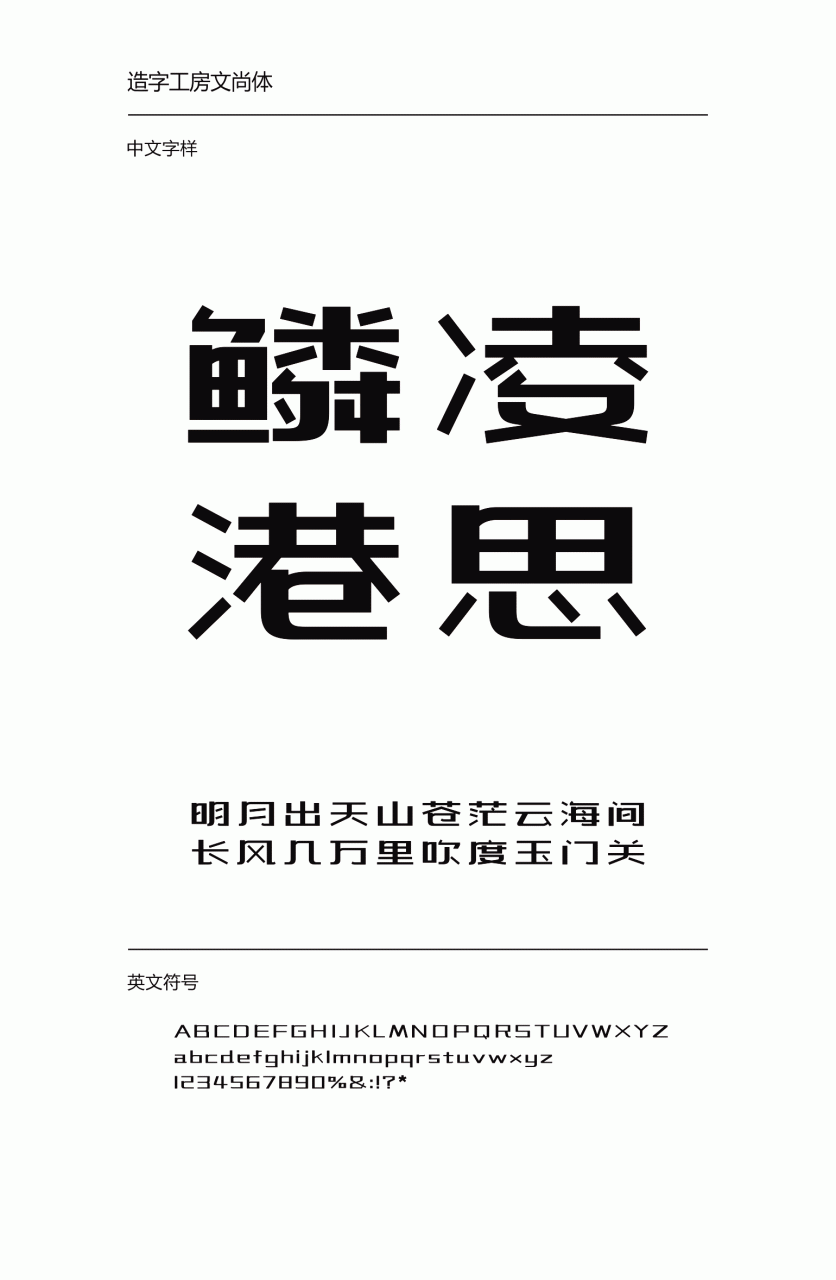
造字工房文尚体,其创意设计风格源于上世纪手绘美术字形,字形扁平,线条粗细变化明显,跌宕有致,短横的倾斜处理,让字形更加个性十足,风格雅致飘逸,任情恣性,自成格调。适用于大标题及个性品牌设计推广等环境。本字体为简体字库,采用OpenType/CID格式,Adobe-GB1-5编码。基于中华人民共和国GB2312-80字符集标准,另按需添加101个汉字。共收容字数6864CJK汉字,ASCII常用字符100个。